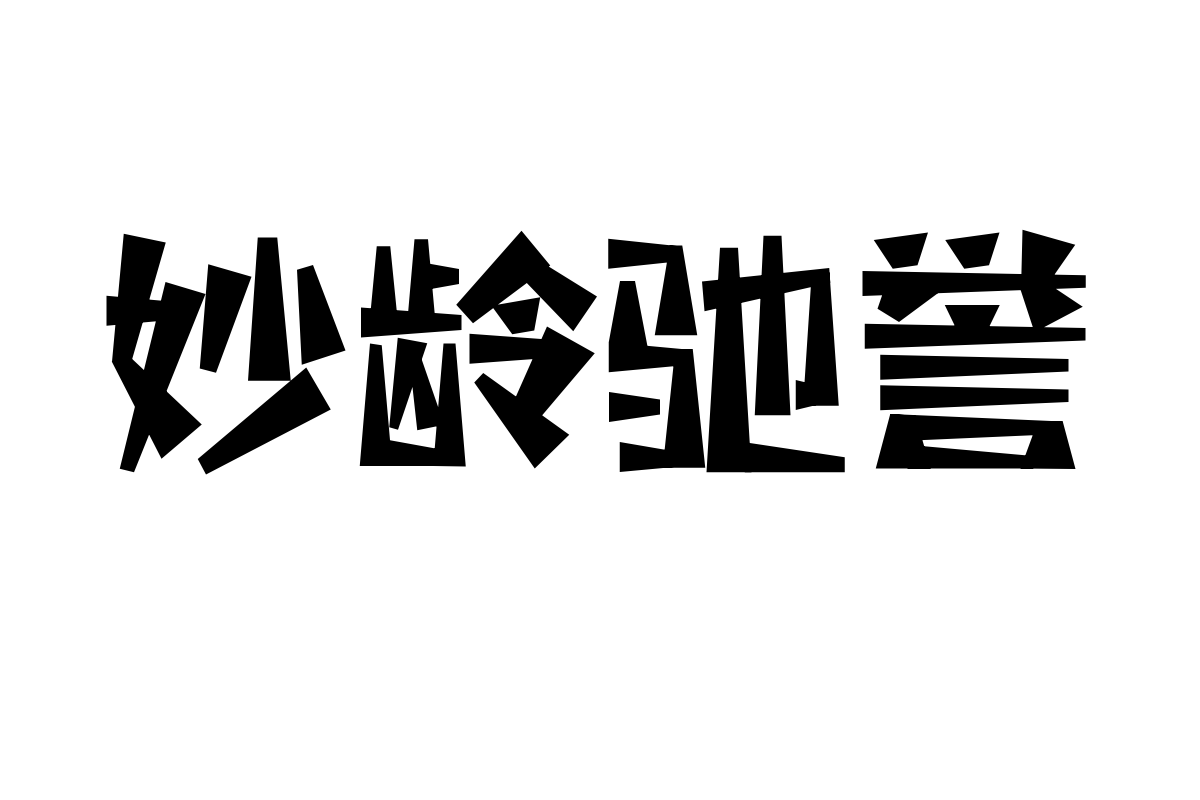
黑简体粗字体是一种常见的中文字体,主要用于印刷和书写。这种字体的特点是字形粗犷,线条粗实,给人一种强烈的视觉冲击感。黑简体粗字体的笔画粗细适中,既有粗犷的线条,又有精细的细节,适合用于各种需要强调文字特点的场合。
黑简体粗字体的特点如下:
1. 字形粗犷:黑简体粗字体的字形线条粗实,给人一种强烈的视觉冲击感,适合用于需要突出文字特点的场合。
2. 笔画粗细适中:黑简体粗字体的笔画粗细适中,既有粗犷的线条,又有精细的细节,使得文字既具有美感又不失实用性。
3. 适用范围广泛:黑简体粗字体适用于各种需要强调文字特点的场合,如广告、宣传册、海报等。同时,也适用于各种需要突出重点的场合,如标题、正文等。
4. 易于识别:黑简体粗字体的字形独特,易于识别,有利于提高阅读效率。
总之,黑简体粗字体是一种具有强烈视觉冲击力和实用性的中文字体,广泛应用于各种需要强调文字特点的场合。